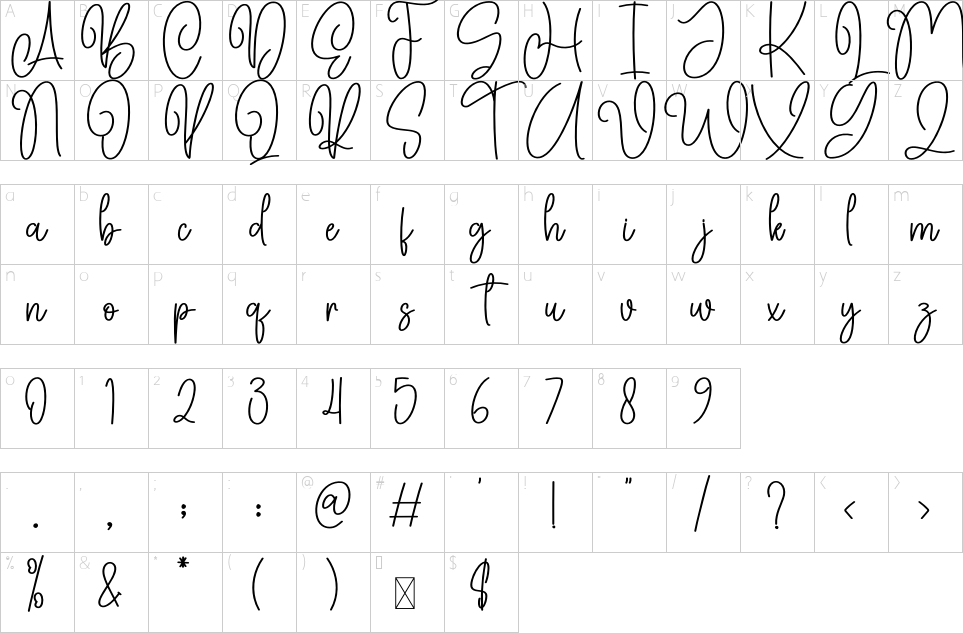
Scotching é uma fonte grátis disponível para Windows e Mac, projetada por scratchones. Esta fonte foi um grande acréscimo para quem busca uma variedade de títulos com traços distintos e elegantes. Com mais de 400 downloads, é evidente que esta font se destaca por sua facilidade de uso e simplicidade. Se você está em busca de uma fonte que combine facilidade de uso com estilo, Scotching é uma escolha excelente. Seu designer não informado trouxe uma proposta que merece ser explorada, oferecendo uma alternativa gráfica versátil para diferentes projetos.